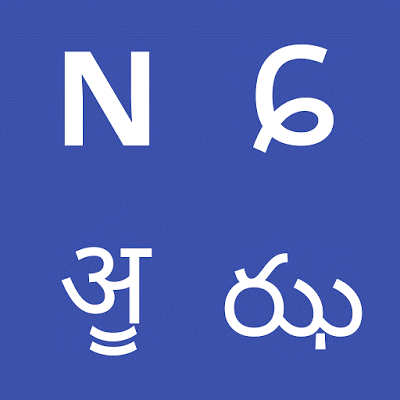
No más tofu, Noto, es una nueva familia de fuente tipográfica digital que contiene unos 110.000 caracteres, cada símbolo Unicode existente, para acoger más de 800 lenguas,
An open source font system for everyone — El proyecto Noto comenzó como una necesidad para los sistemas operativos Android y Chrome OS. Cuando comenzamos no éramos conscientes de la magnitud del desafío. Requirió diseñar y comprar cientos de lenguas y la experiencia de expertos en escritura, y la colaboración de expertos en tipografía como Monotype y Adobe además de una extensa red de colaboradores y voluntarios. En árabe, por ejemplo, cada carácter tiene cuatro glifos (esto es, formas que puede tener un carácter) que depende del texto que viene a continuación. En lenguas indoarias los glifos pueden cambiar de posición e incluso dividirse en dos dependiendo del texto circundante.
El proyecto ha necesitado cinco años hasta verse completado, y el resultado es una tipografía bonita y unificada, «para todos», que resuelve el problema de los «cuadraditos» o los espacios en blanco cuando se abre un texto que contiene símbolos o caracteres que no existen en una fuente tipográfica específica. La eliminación de esos cuadraditos como de tofu son los que dan nombre a la tipografía Noto.